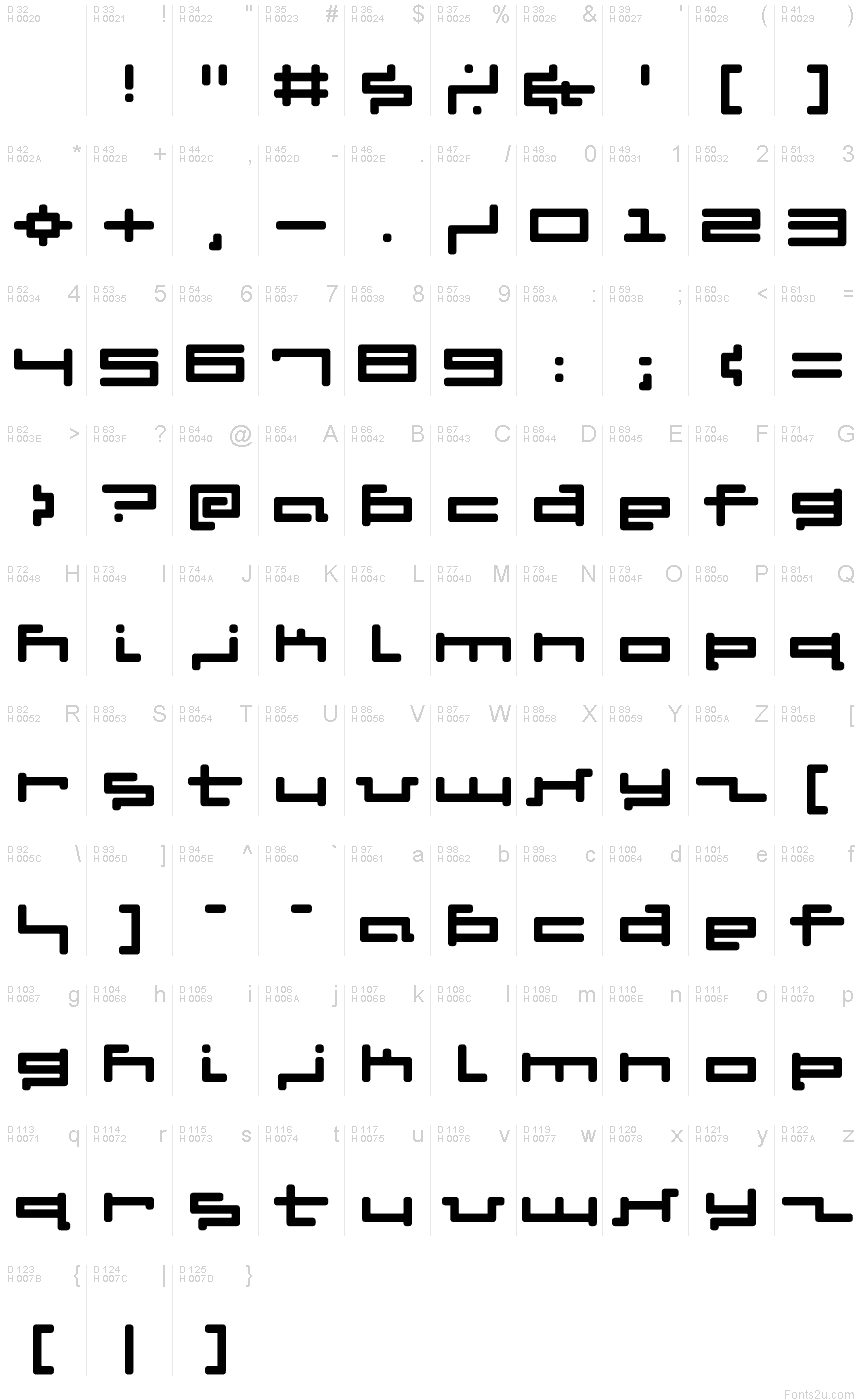
V5 Cuadra 2 Round, entworfen von Roberto Christen für vFive, ist eine kostenlose, abgerundete Techno-Display-Schrift mit einem eleganten, modularen Rhythmus, der an das digitale Flair früher Hardware erinnert. Die Buchstaben basieren auf breiten, quadratischen Pfaden mit weichen Ecken und langen horizontalen Schwüngen, was der Schrift einen ruhigen, maschinellen Fluss verleiht, anstatt einer aggressiven Sci-Fi-Optik.
Sie passt perfekt in Branding-Konzepte, die von Benutzeroberflächen inspiriert sind, sowie in Musik-Flyer, Spiel-Titelkarten, Plakatüberschriften und kurze Beschriftungen auf Verpackungen, bei denen diese durchgehende, fast wie eine Bahn verlaufende Bewegung den Grundton vorgibt. Nutzen Sie sie für kompakte Logos, Cover-Texte oder knappe Hinweise, wenn das Schriftbild technisch durchdacht, glatt und mit einem Hauch von Retro-Futurismus wirken soll.